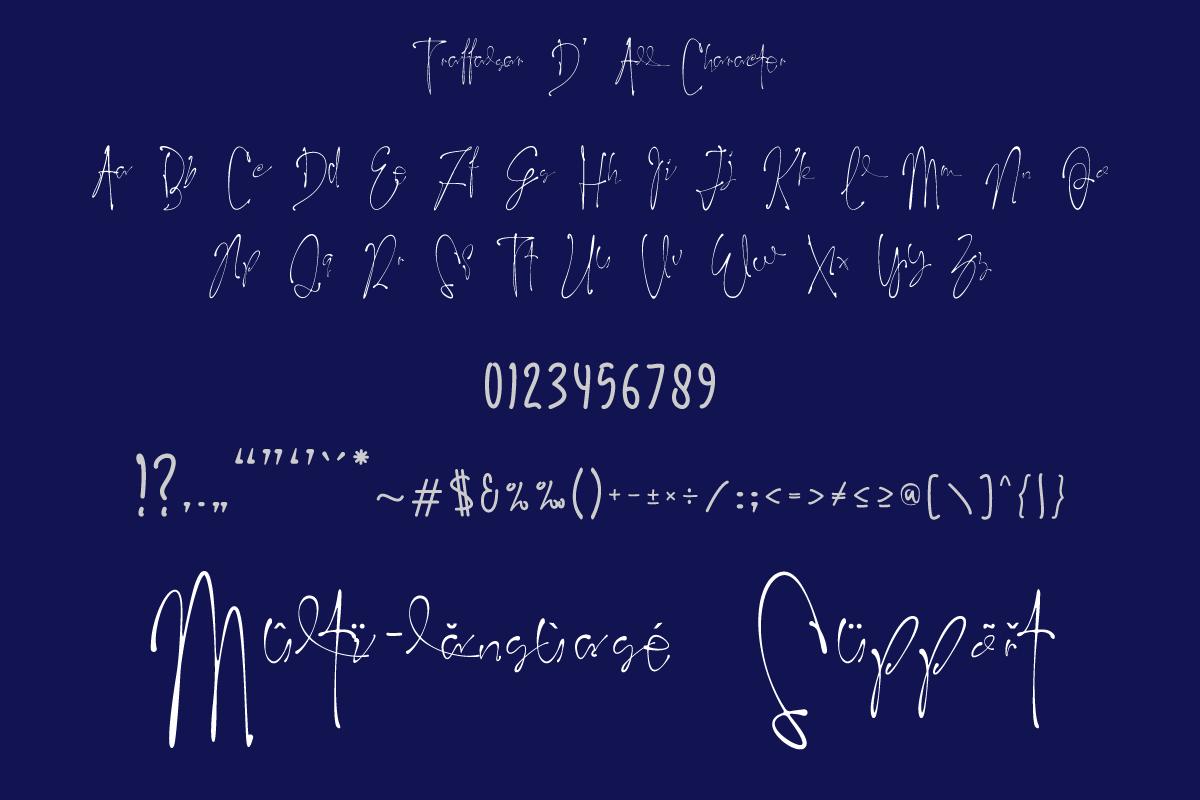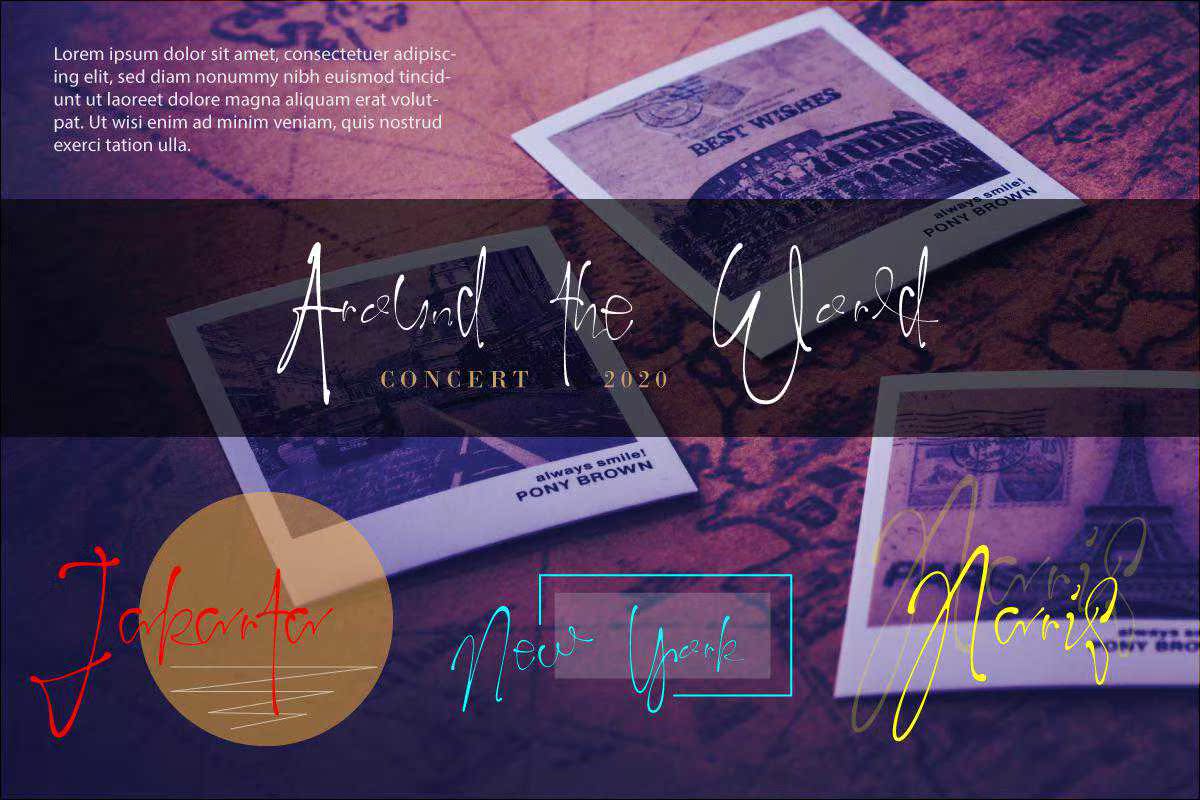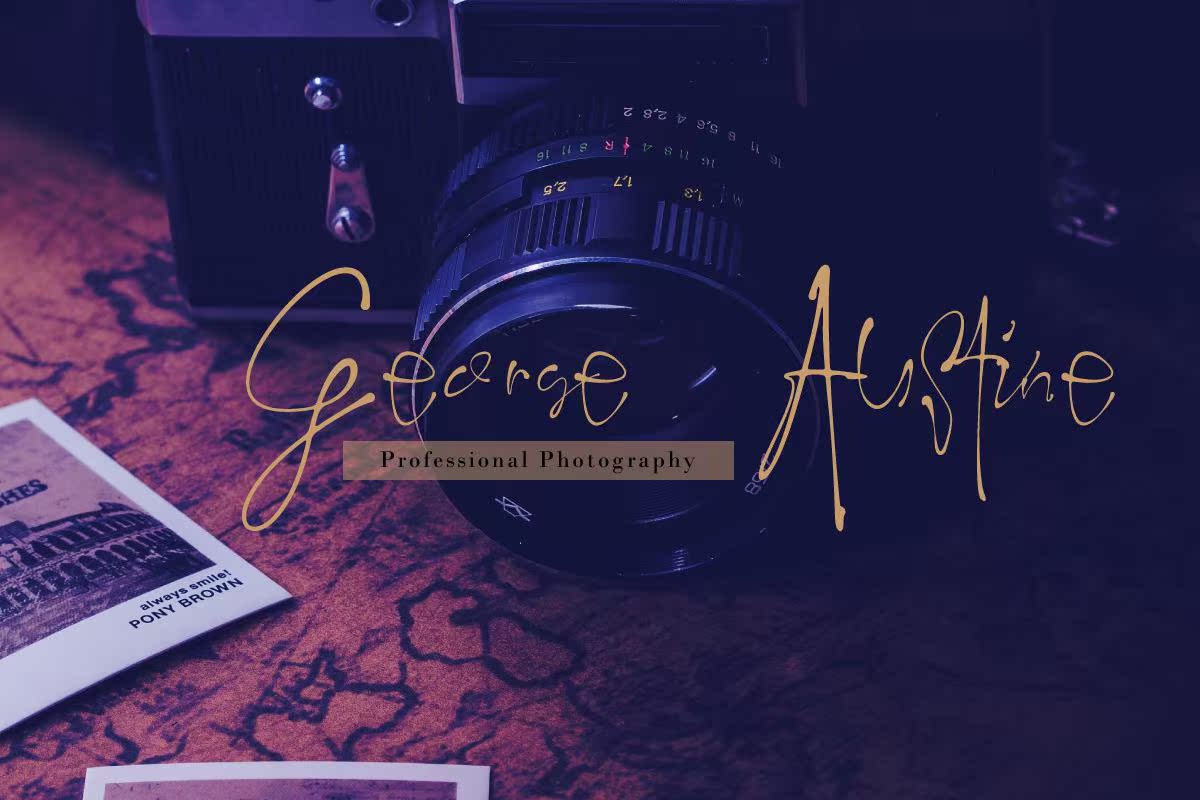
TraffalgarD’s Signature是一款传统的手写字体,而非自然风格。这款收藏品是个人品牌的完美之选,旨在使用商标和名片。TraffalgarD’s Signature可用于各种用途,包括广告宣传、平面设计、印刷设计、网站设计、徽标、品牌推广,TraffalgarD’s Signature是一款传统的手写而非自然风格的签名。这款收藏品是个人品牌的完美之选,旨在使用水牌和名片。TraffalgarD’s Signature可用于各种目的,如宣传、平面设计、印刷设计、网站设计、徽标、品牌等。